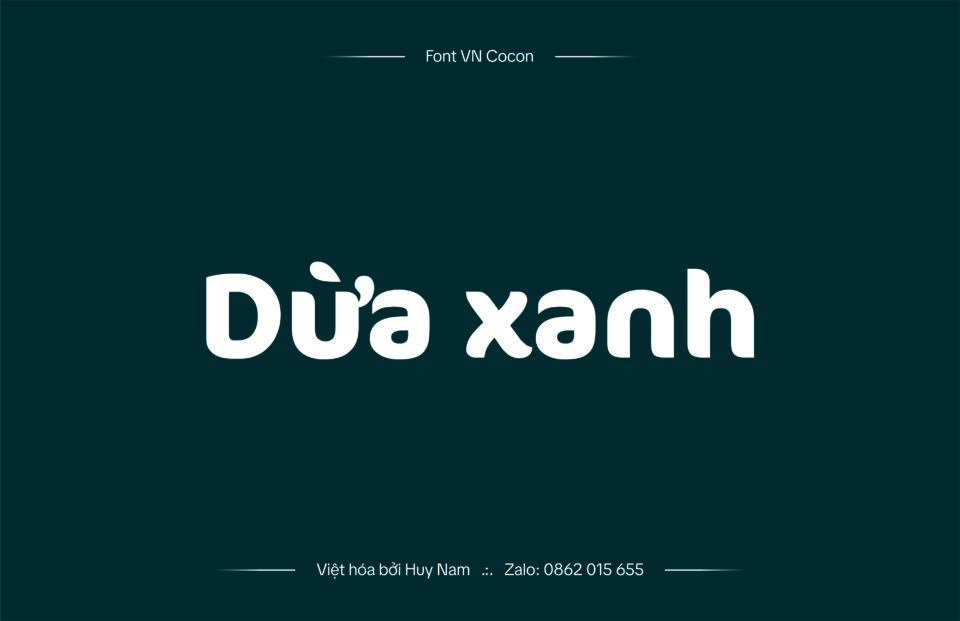
Font Việt hóa VN Cocon
Giới thiệu về bộ Font Việt hóa VN Cocon trong thiết kế
Trong thế giới đồ họa hiện đại, việc lựa chọn Font Miễn Phí phù hợp đóng vai trò quyết định đến sự thành công của một tác phẩm. Một trong những bộ chữ được cộng đồng designer tại Việt Nam ưa chuộng nhất chính là Font Việt hóa VN Cocon. Đây là một phông chữ mang phong cách bo tròn độc đáo, tạo cảm giác thân thiện, mềm mại nhưng vẫn giữ được nét hiện đại và chuyên nghiệp. Với khả năng hỗ trợ tiếng Việt hoàn chỉnh, bộ font này đã giải quyết triệt để nỗi lo lỗi dấu khi soạn thảo văn bản hay thiết kế banner cho các sự kiện học đường và doanh nghiệp.
Đặc điểm nổi bật của Font Việt hóa VN Cocon
Sự khác biệt của Font Việt hóa VN Cocon nằm ở cấu trúc chữ không chân với các đường cong được xử lý mượt mà. Phông chữ này không chỉ dễ đọc mà còn mang lại cảm giác trẻ trung, rất phù hợp cho các tiêu đề lớn hoặc các câu trích dẫn mang tính khơi gợi cảm hứng. Các chuyên gia font tại Việt Nam đánh giá cao khả năng ứng dụng đa dạng của nó, từ việc làm bìa sách giáo khoa cho đến các thiết kế áo lớp sinh động. Việc sử dụng font chữ này giúp các bạn học sinh và giáo viên dễ dàng tạo ra những tài liệu học tập bắt mắt mà không tốn quá nhiều công sức căn chỉnh.
Lý do bạn nên sở hữu Font Việt hóa VN Cocon cho dự án
Việc cài đặt và sử dụng Font Việt hóa VN Cocon mang lại nhiều lợi ích thiết thực cho người dùng, đặc biệt là những người mới bắt đầu làm quen với thiết kế. Thứ nhất, bộ font này đã được tối ưu hóa bảng mã Unicode, đảm bảo hiển thị tốt trên mọi phần mềm từ Office cho đến Adobe Photoshop hay Canva. Thứ hai, tính thẩm mỹ của nó giúp nâng tầm các sản phẩm in ấn, tạo điểm nhấn thu hút người xem ngay từ cái nhìn đầu tiên. Đối với môi trường giáo dục, sự mềm mại của bộ chữ giúp các bài giảng điện tử trở nên gần gũi và bớt khô khan hơn đối với học sinh các cấp.
Hướng dẫn sử dụng font hiệu quả trong trình bày
Để phát huy tối đa vẻ đẹp của Font Việt hóa VN Cocon, bạn nên kết hợp nó với các màu sắc tươi sáng hoặc phối cùng một font chữ có chân mảnh để tạo sự tương phản. Khi dùng làm tiêu đề, hãy tăng kích thước chữ lớn hơn một chút để các đường bo tròn đặc trưng được hiển thị rõ nét nhất. Đừng quên chú ý đến khoảng cách giữa các chữ cái nhằm đảm bảo sự thông thoáng cho bố cục tổng thể. Việc hiểu rõ đặc tính của font sẽ giúp bạn truyền tải thông điệp một cách trọn vẹn và đầy tính nghệ thuật.
Kết luận và trải nghiệm Font Việt hóa VN Cocon ngay hôm nay